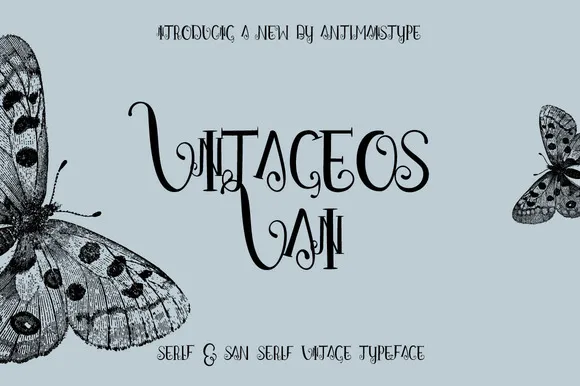
Font - VINTAGEOS VAIN
A fonte ‘VINTAGEOS VAIN’ é uma elegante escolha para designers e criadores digitais que buscam um estilo único na categoria de Blackletter fonts. Inspirada nos tempos vitoriosos, essa fonte traz charme vintage sem perder a funcionalidade moderna. Com seu design curioso e arredondado, VINTAGEOS VAIN oferece uma medida sofisticada para qualquer projeto. Disponível em formatos de ficheiro TTF, OTF e web (em formato EOT, SVG, WOFF), ela é ideal tanto para uso tradicional quanto na web. Suportando o alfabeto latino, a fonte também inclui caracteres alternativos como prew, permitindo uma personalização adicional. Com um tamanho de arquivo de 5,86 MB, VINTAGEOS VAIN garante velocidade de carregamento satisfatória para uma experiência mais suave em sua página. Ideal para criar o texto de forma elegante e atraente em portfólios pessoais, sites ou qualquer outro projeto onde um toque vintage se encaixa perfeitamente no estilo do design. Seja você um designer de gráficos, web designer ou criador digital que busca algo verdadeiramente único para seu próximo trabalho, VINTAGEOS VAIN certamente não lhe decepcionará.